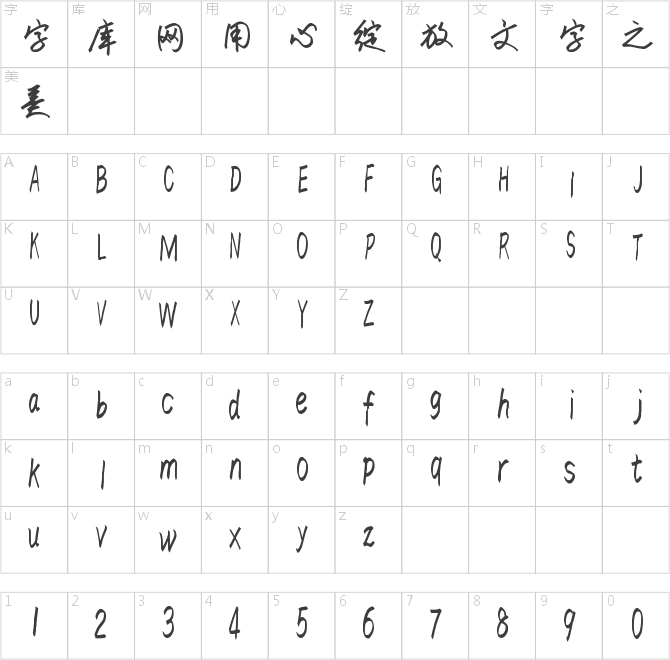
漢標景晨新POP體 詳情頁
漢標景晨新POP體
漢標景晨新POP體字體pop字體字庫是一款讓人賞心悅目、百看不厭的中文字體,適合各類廣告和產(chǎn)品包裝設(shè)計應(yīng)用,字體大小10.31MB,格式為ttf字體,上傳用戶是漢標文創(chuàng),作者/版權(quán)方為漢標字庫